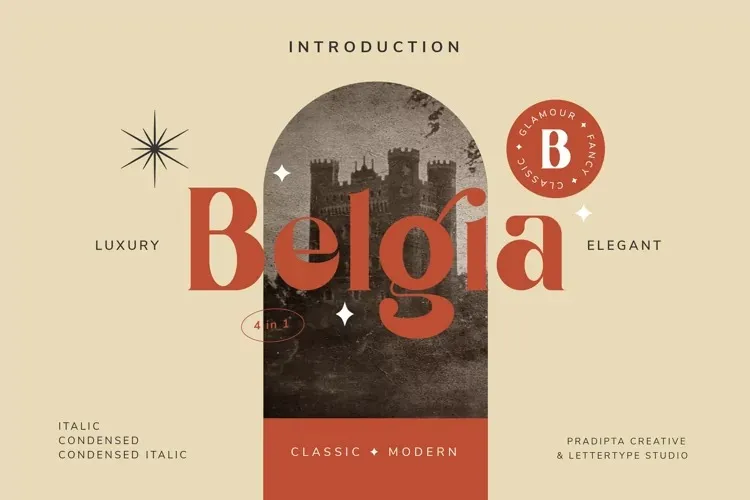
Belgia Font – Fonte Grátis
Belgia Font
A Belgia Font é uma escolha perfeita para quem busca uma fonte serif que combine a sofisticação do passado com as características modernas dos dias atuais. Desenvolvida pelo site de design 99designs, esta fonte oferece um toque elegante e luxuoso aos projetos mais prestigiados. Com sua combinação perfeita entre formas serifadas clássicas e elementos modernos, a Belgia Font é ideal para criações que exigem uma aparição de alto padrão. Suas linhas suaves e detalhes sofisticados ajudam seus trabalhos a ganhar um toque especial em aplicativos como logotipos, marcas, roupas de marca, signagens, cartazes e até mesmo convites de casamento. Acredite, esta font não é apenas uma adição para sua biblioteca de fonts; ela é uma grata surpresa que pode transformar suas criações digitais em obras de arte. Não perca essa oportunidade de incorporar um toque único e elegante a seus projetos.